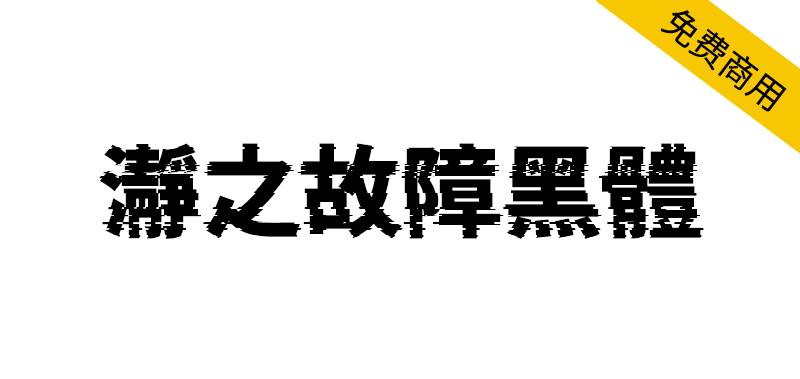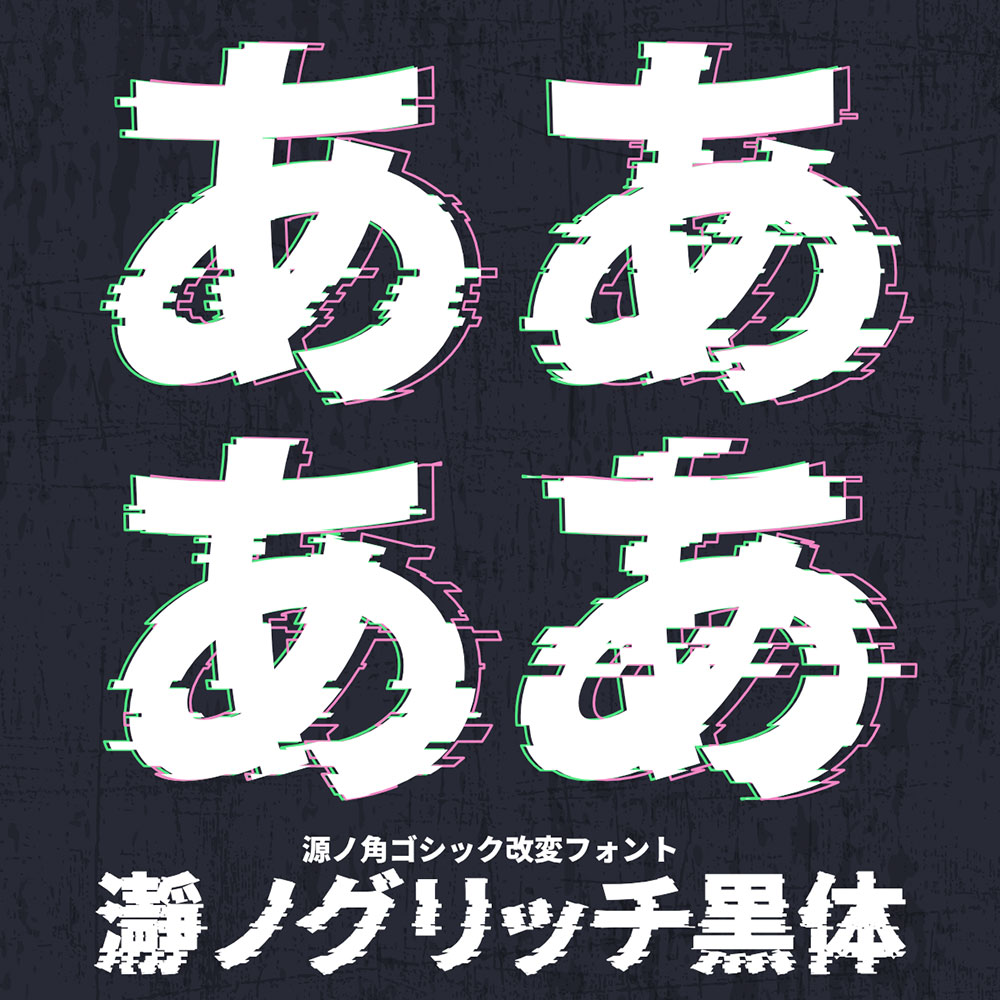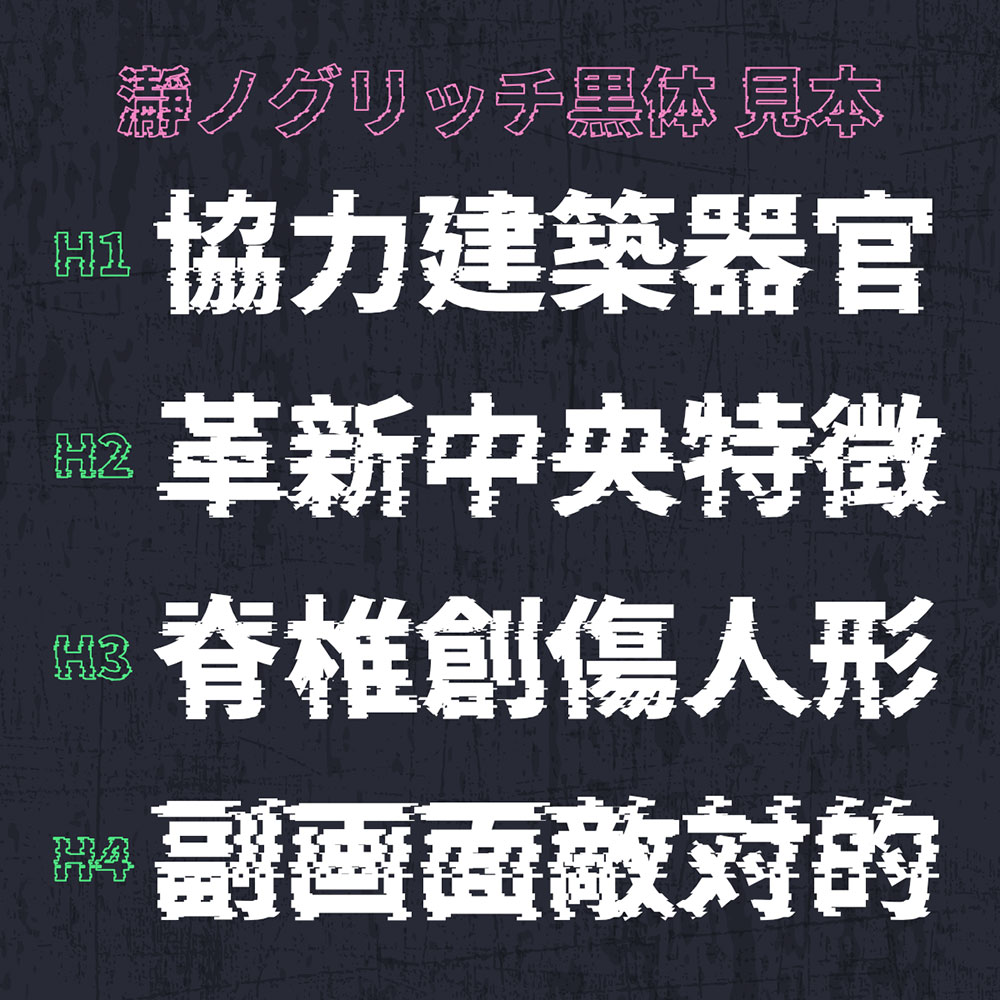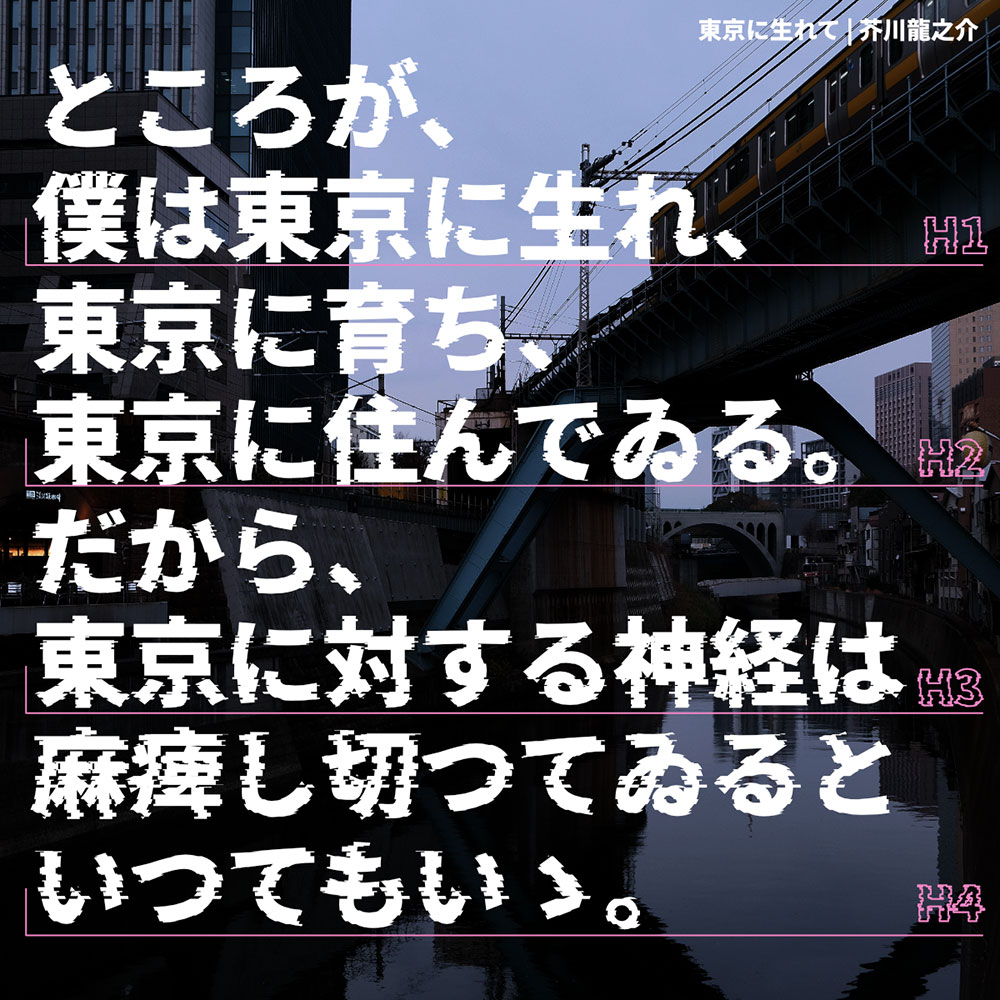
【瀞之故障黑体】基于思源黑体制作的故障特效字体
想要让你的设计作品瞬间充满赛博朋克风格?瀞之故障黑体这款基于思源黑体打造的故障特效字体,以其独特的断裂、错位和像素化效果,为你的创意注入强烈的数字艺术冲击力。更令人惊喜的是,这款视觉震撼的字体完全免费商用,可自由再分发与修改,为设计师们提供了全新的创作可能性。
【瀞之故障黑体】基于思源黑体制作的故障特效字体
瀞之故障黑体(瀞ノグリッチ黒体)是一款基于思源黑体进行艺术处理,加工成具有故障特效的黑体字体,遵循Adobe-Japan1-6标准(部分字符可能存在缺失),依据SIL OPEN FONT LICENSE Version 1.1协议授权发布,可商用、可自由再分发、修改。